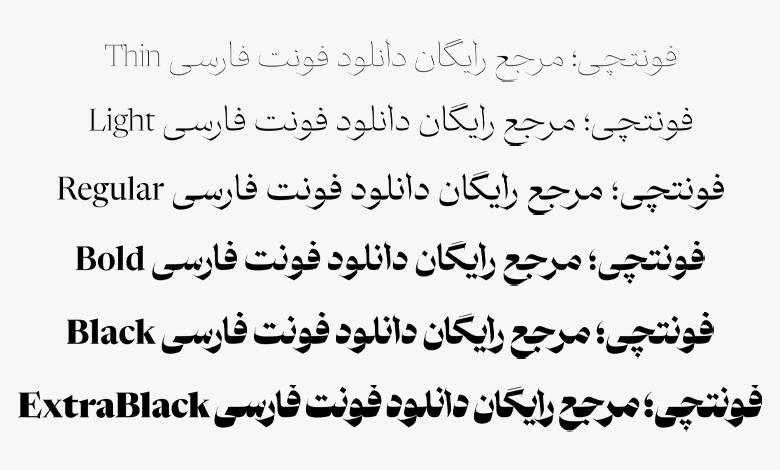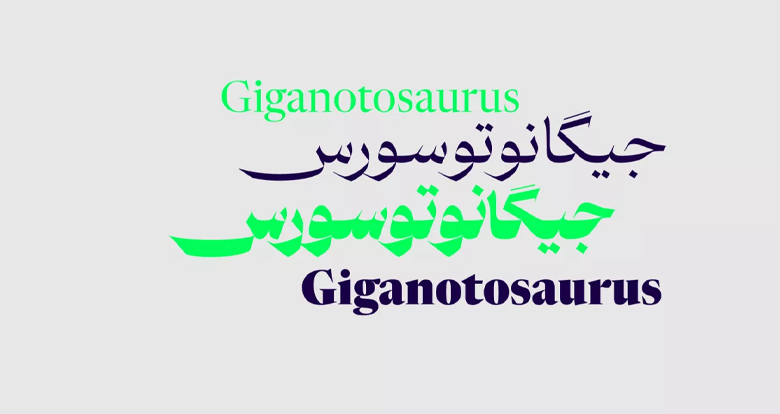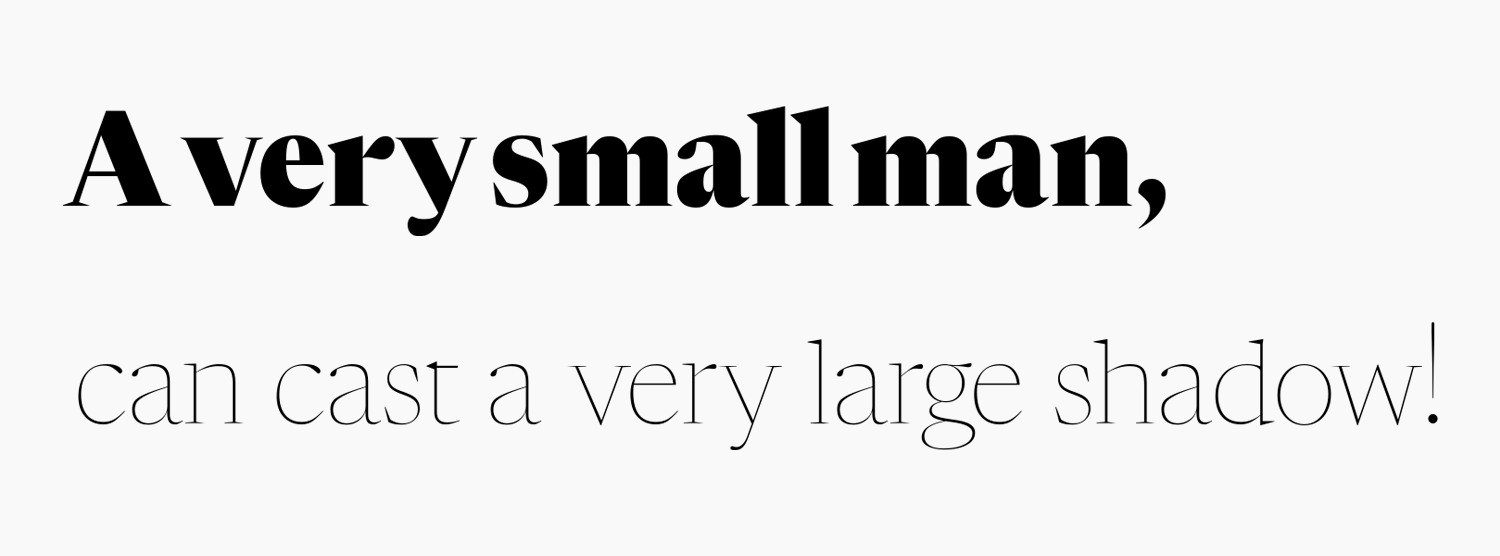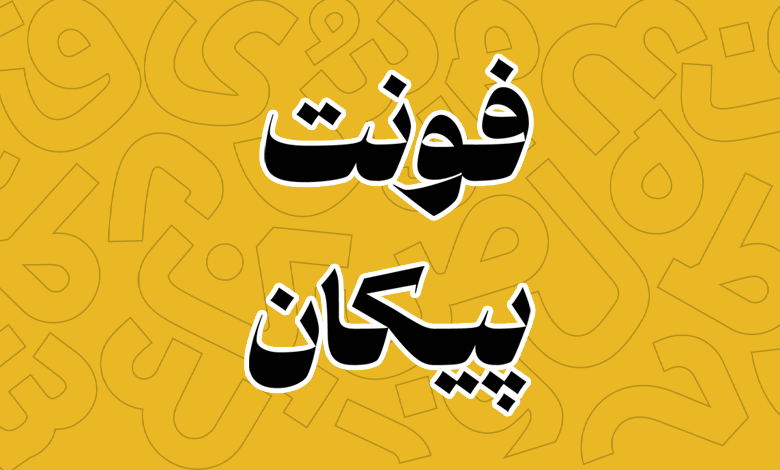
فونت پیکان (Paykan)
فونت پیکان (به انگلیسی: Paykan) در دسته فونت عناوین و مناسب برای تیتر طراحی شده است که میتوانید در طرحهای گرافیکی با متون کوتاه که نیاز به قلم نسخ دارید از آن استفاده کنید. فونت پیکان رایگان نبوده و با توجه به وزنهای ۶ گانه و پشتیبانی وریبل در ۳ بسته قابل خریداری است.
ایده شکلگیری فونت پیکان توسط طراح آن، رضا بختیاری فرد؛ بر اساس قلم شفیق صورت گرفته است. جسارت و لهجهای که در فونت شفیق بوده سبب شد تا طراح فونتی مشابه آن، اما با اغراق بسیار بیشتر را طراحی کند که پر از تغییرات ناگهانی، خصوصا خطوط باریک بیش از حد در عین منحنیهای قطور است.
در ادامه این نوشته از سایت فونتچی به نقد و بررسی کامل فونت پیکان خواهیم پرداخت؛ فونتی که میتوانید از آن بیشتر در دنیای مد و فشن استفاده کنید تا برندهای لوکس را بیشتر در معرض نمایش و توجه قرار دهید.
بررسی و دانلود فونت پیکان (Paykan)
فونت پیکان که برگرفته از خط نسخ است، پر از تغییرات ناگهانی است. در این فونت حروف دارای تغییراتی ناگهانی و در عین حال جدی هستند که کنتراست آنها از نظر ضخامت بسیار افراطی صورت گرفته است؛ طوری که در عین حال که حروف پهن را دنبال میکنید، به ناگاه این حروف پهن در منحنی و شکستگیها پهنای خود را تا مرز خطی شدن به یکباره از دست میدهند.
فونت Paykan دارای اسکلتی ضخیم است که خطوط صاف آن را همراهی میکنند. هرچند که تنه حروف در منحنیها بسیار نرم بهنظر میرسد، اما در شکستگیها بسیار تیز و برنده هستند. چنین نوع طراحی را در فونت دیگری، اما با ضخامت کمتر و منحنیهای ملایمتر در فونت دوران مشاهده کردهایم.
سبک طراحی و وزن فونت پیکان
فونت پیکان مناسب نوشتههای کوتاه و تیترهایی است که باید در یک لحظه جلب توجه کرده و تاثیر خود را روی مخاطب بگذارد. از اینرو میتوانید در طراحیهای مرتبط با فشن و برای برندهای لوکس از آن استفاده کنید. همچنین بهخاطر لهجهاش برای محصولات وارداتی هم مناسب است.
از سوی دیگر فونت پیکان بر اساس همین نوع طراحی، این نام را دریافت کرده تا یادآور خودروی خاطرهانگیز دهههای ۶۰ و ۷۰ در ایران باشد که فیس لیفتی از خودروی هیلمن هانتر بود. لذا این فونت جنبه نوستالژی هم دارد.
فونت پیکان را میتوانید در ۶ وزن مختلف نازک تا خیلی سیاه دریافت کنید. این ۶ وزن فونت هرچه که به وزن آنها افزوده میشود، منحنیها چاقتر شده و در عینحال شکستگیها نقاط تیز و برنده خود را در همان ساختار خطی و بسیار نازک حفظ میکنند.
پشتیبانی از ۵ زبان مختلف
فونت فارسی پیکان محدود به این زبان نیست و میتوان گفت که پشتیبانی کاملی از چندین زبان خاورمیانهای و لاتین در آن پیاده سازی شده است. فونت عربی، اردو، و کردی دیگر زبانهایی هستند که قلم پیکان از آنها پشتیبانی میکند.
در این زبانها که بر پایه رسم خط فارسی هستند، پشتیبانی حروف بر اساس همین زبان بوده و در هر یک از ساختار حروف همچون زبان عربی برای «ک، ی، ه، ؤ، ئ» گلیفهای آنها نیز طراحی شده تا کاملا هماهنگ با هر زبان باشد. یا مثلا در زبان کردی که پر از کاراکترهای تزئینی و اعراب روی حروف است، چنین مواردی نیز پیاده سازی شده است.
فونت paykan انگلیسی از قلم Newsreader وام گرفته شده است که صرفا مقداری تغییرات در تناسب و ضخامت حروف به منظور هماهنگی بیشتر با قلم فارسی صورت گرفته است.
فونت انگلیسی پیکان، محدود به این زبان لاتین نبوده و میتوانید در زبانهای دیگری همچون ترکی استانبولی، فرانسه و… که بر اساس رسم خط انگلیسی هستند استفاده کنید. چرا که حروفی همچون «ı, ğ, ç, ü» در این قلم پشتیبانی میشود.
پشتیبانی در تمامی زبانهای خاورمیانهای برای اعراب کامل بوده و متناسب با هر زبان اعراب نیز برای حروف قرار دارد. همچنین این فونت از زبان جاوی نیز پشتیبانی میکند.
دارای حروف و ترکیبات جایگزین
دیگر قابلیت فونت پیکان پشتیبانی از حروف با شکل متفاوت و ترکیباتی است که امکان تایپ کلمات با ظاهر مختلفی را در اختیار شما قرار میدهد. این مدل طراحی برای تبلیغات کاملا ضروری است و با توجه به اینکه طراحی فونت پیکان بر مبنای فونتی مناسب برای دنیای مد و پوشاک طراحی شده تا در یک نگاه جلب توجه کند، تایپ متفاوت برخی کلمات به بهتر شدن این رویکرد کمک میکند.
همانطور که در تصویر بالا مشاهده میکنید، حروف و ترکیباتی مثل «ـن، ـی، ـر، ـی، ک، م» امکان تایپ با ظاهری متفاوت را در ابتدا، میانه یا انتهای کلمات به شما خواهند داد.
با دانلود فونت پیکان برای فتوشاپ میتوانید از طریق تنظیمات اپنتایپ به تمامی این گلیفها و ترکیبات دسترسی داشته و با استفاده از روشهایی که برای تایپ آنها وجود دارد، کلمات را در اشکال مختلفی تایپ کنید. چنین ویژگی برای کسانی که از فونت paykan برای کارهای گرافیکی، بهویژه در حوزه تبلیغات استفاده میکنند مناسب است.
فونت پیکان وریبل و متغیر
قابلیت دیگر فونت پیکان که برای استفاده در وب فونت و موبایل بسیار کاربردی است، پشتیبانی از نسخه متغیر است. با نصب فونت وریبل پیکان در سایت یا حتی نرمافزارهای گرافیکی به جای اینکه هر ۶ وزن این فونت و همچنین فونت مخصوص برای اعداد هک شده فارسی را نصب کنید، صرفا میتوانید با نصب یک فایل کلیه وزنها را داشته باشید.
نسخه متغیر قلم پیکان امکان تغییر وزن حروف را در محدوده ۱۰۰ تا ۹۰۰ به شما خواهد داد که میتوانید وزنهای لاغر تا خیلی ضخیم را با استفاده از دستورات CSS برای وب و برای محیط نرمافزار از طریق تنظیمات Open Type انجام دهید.